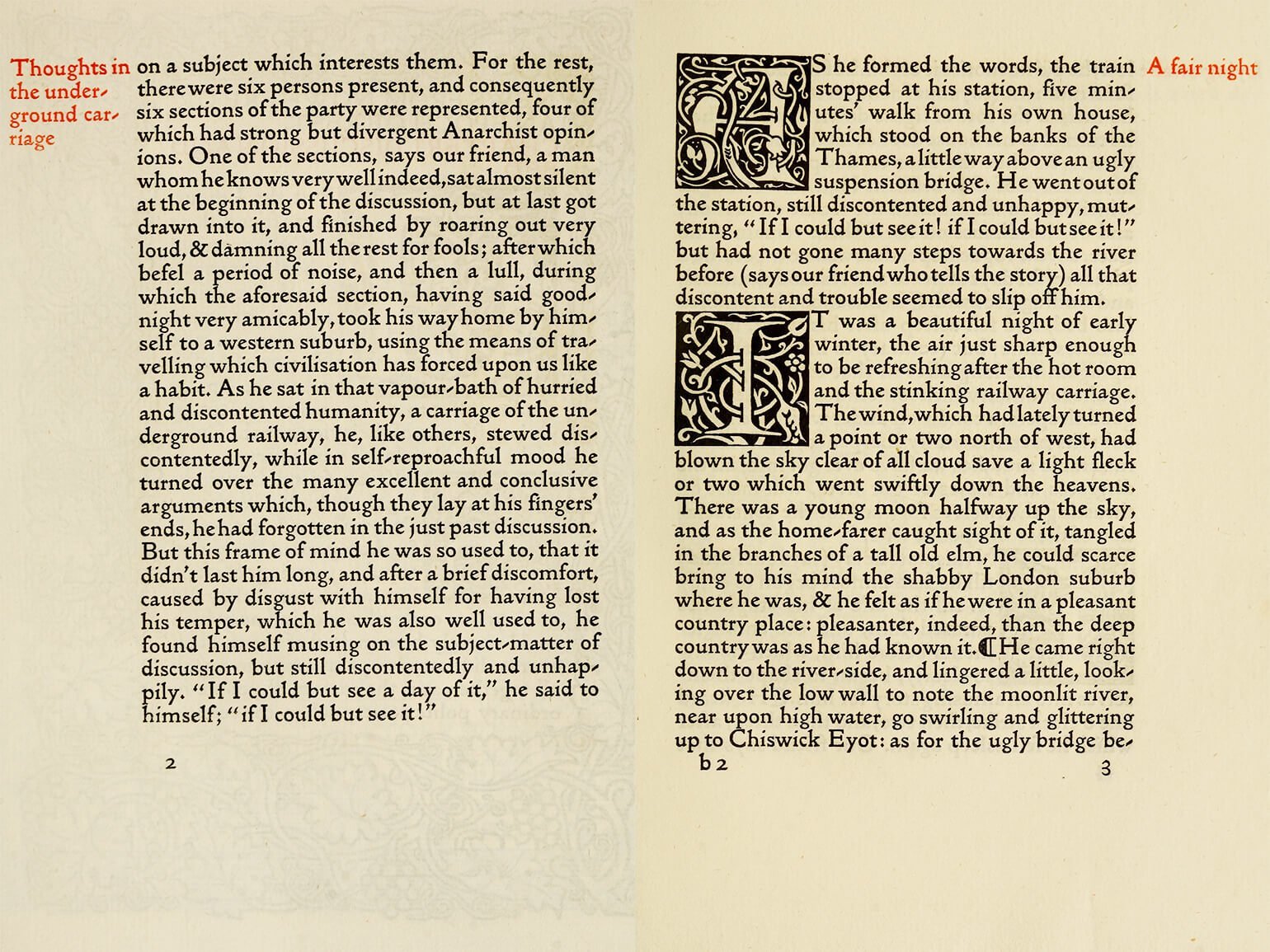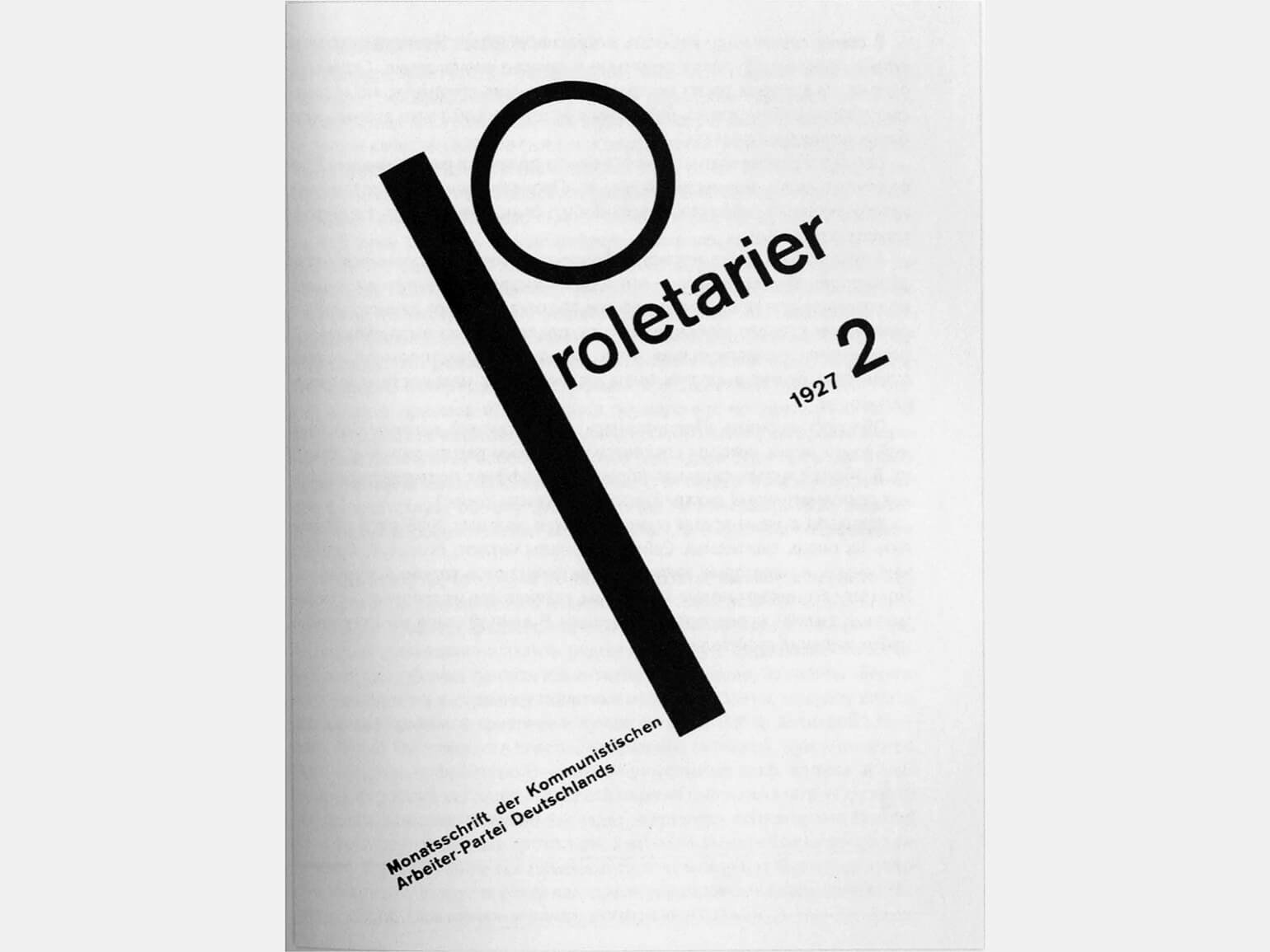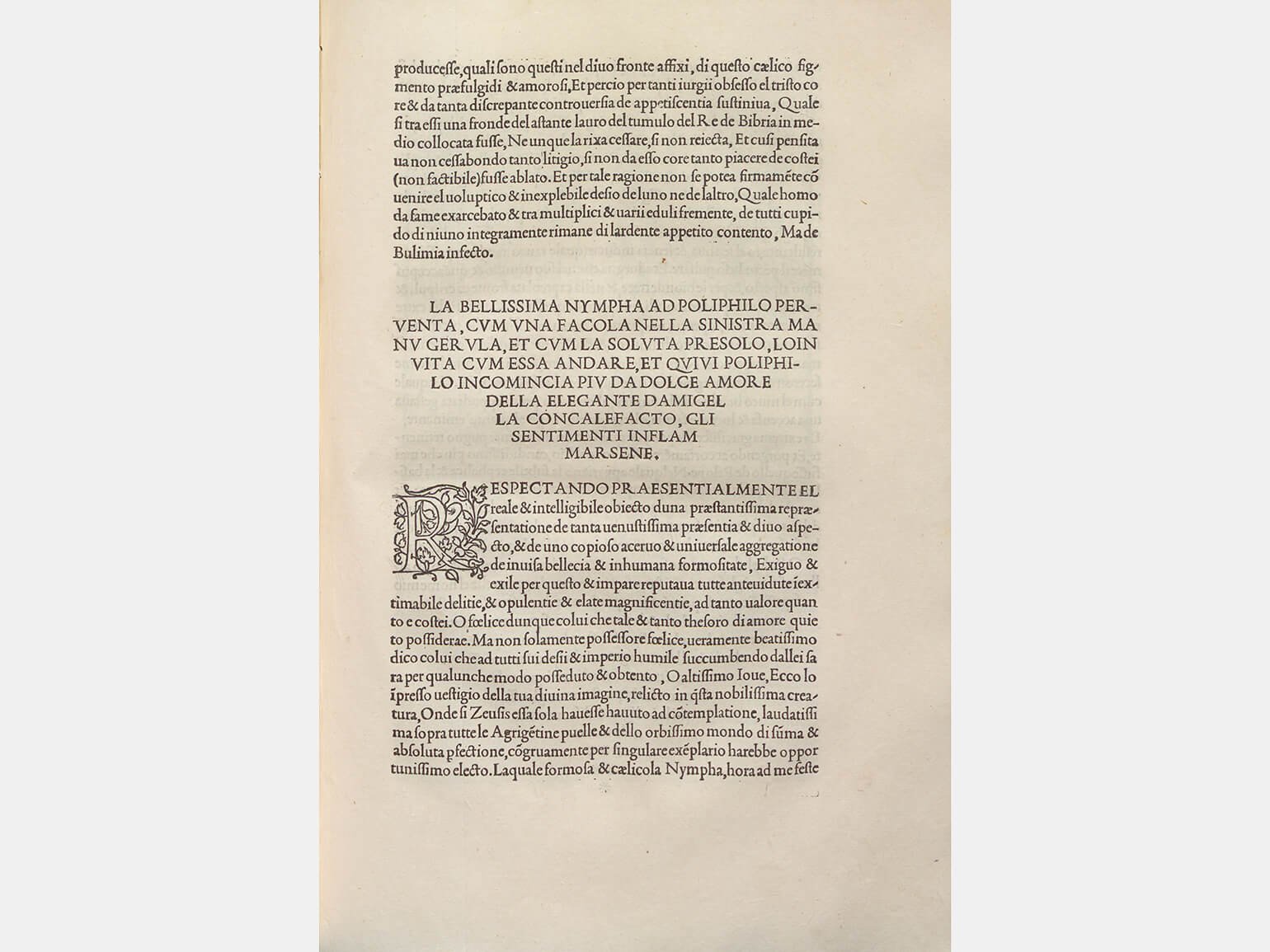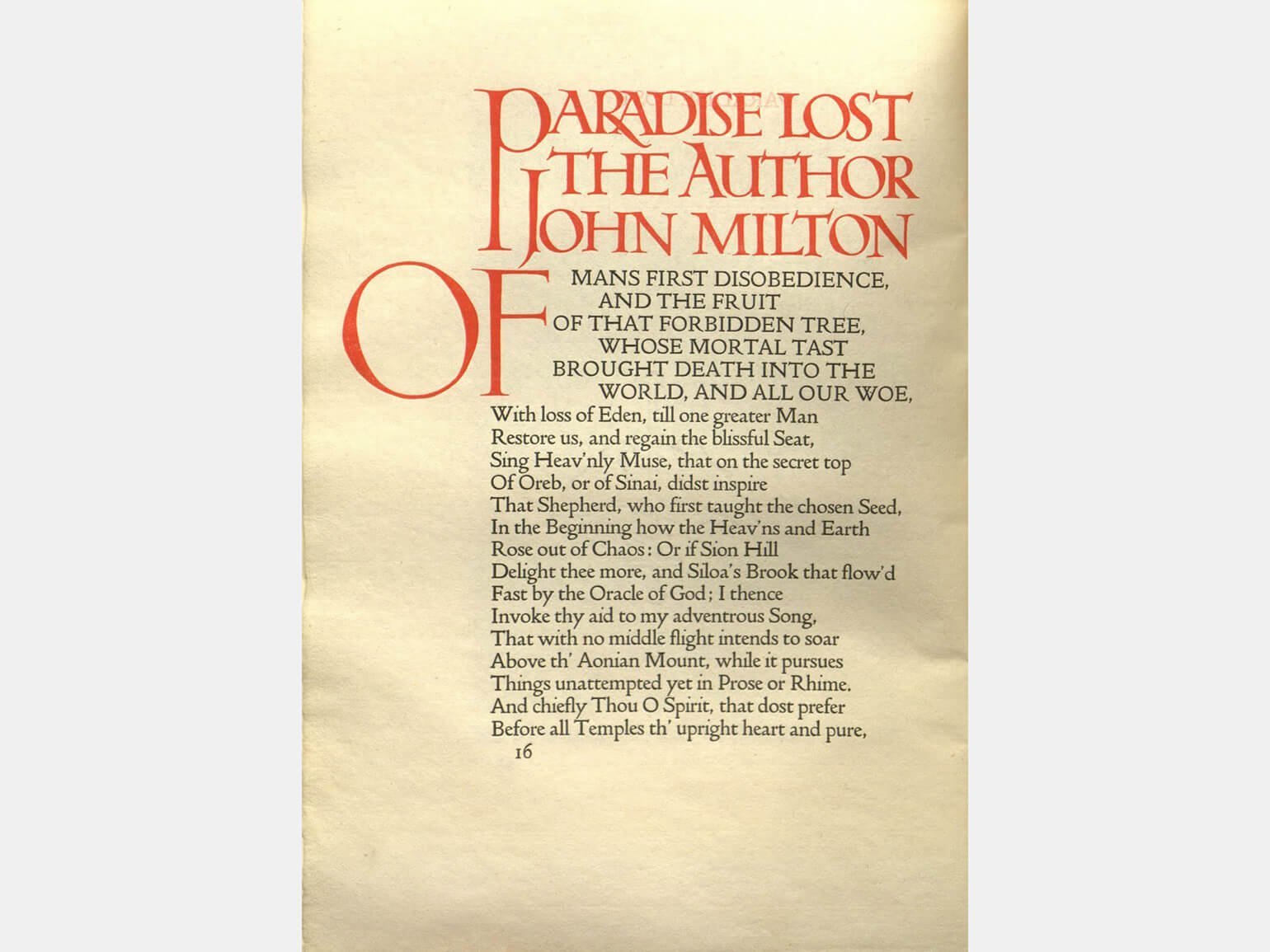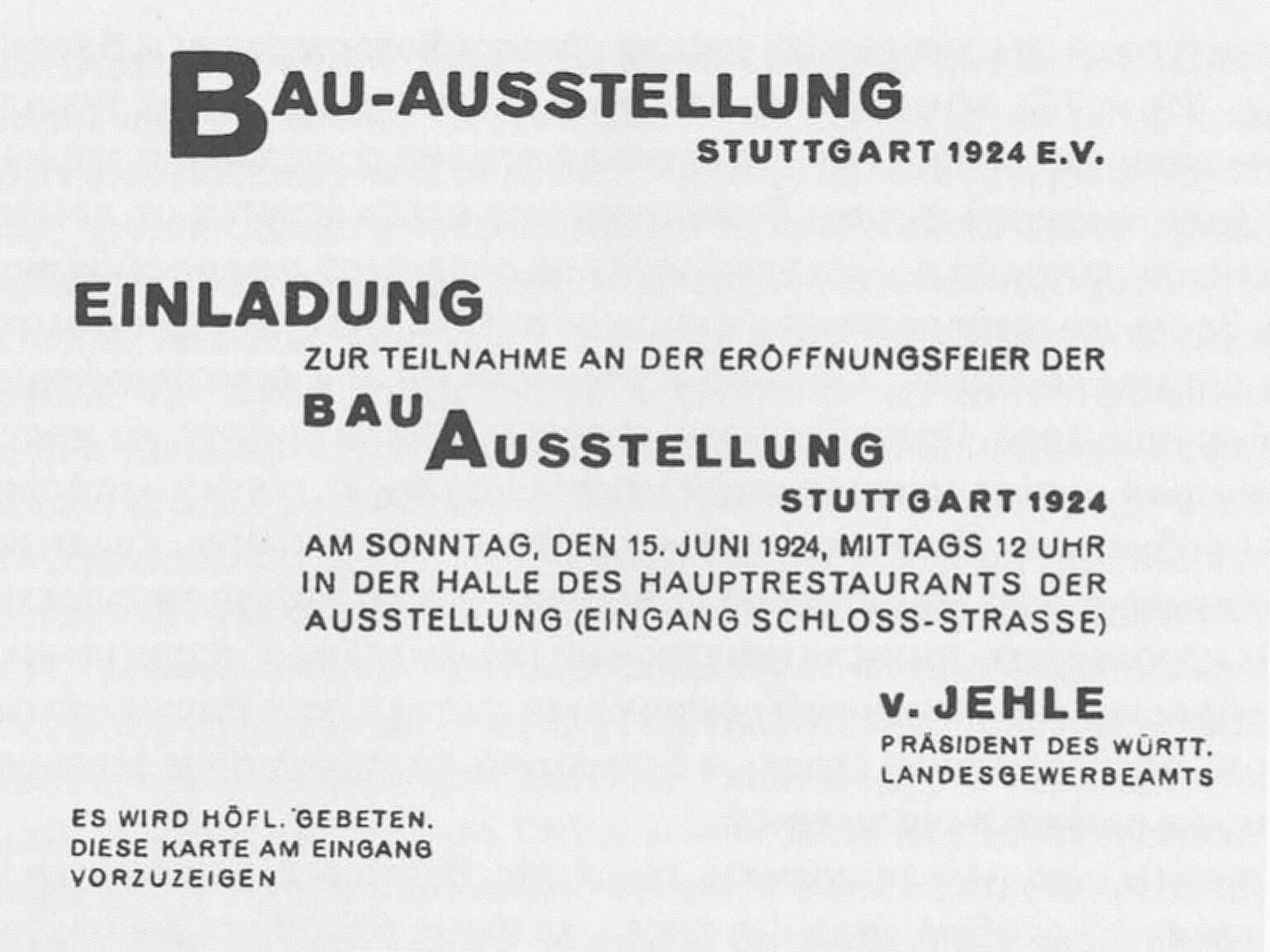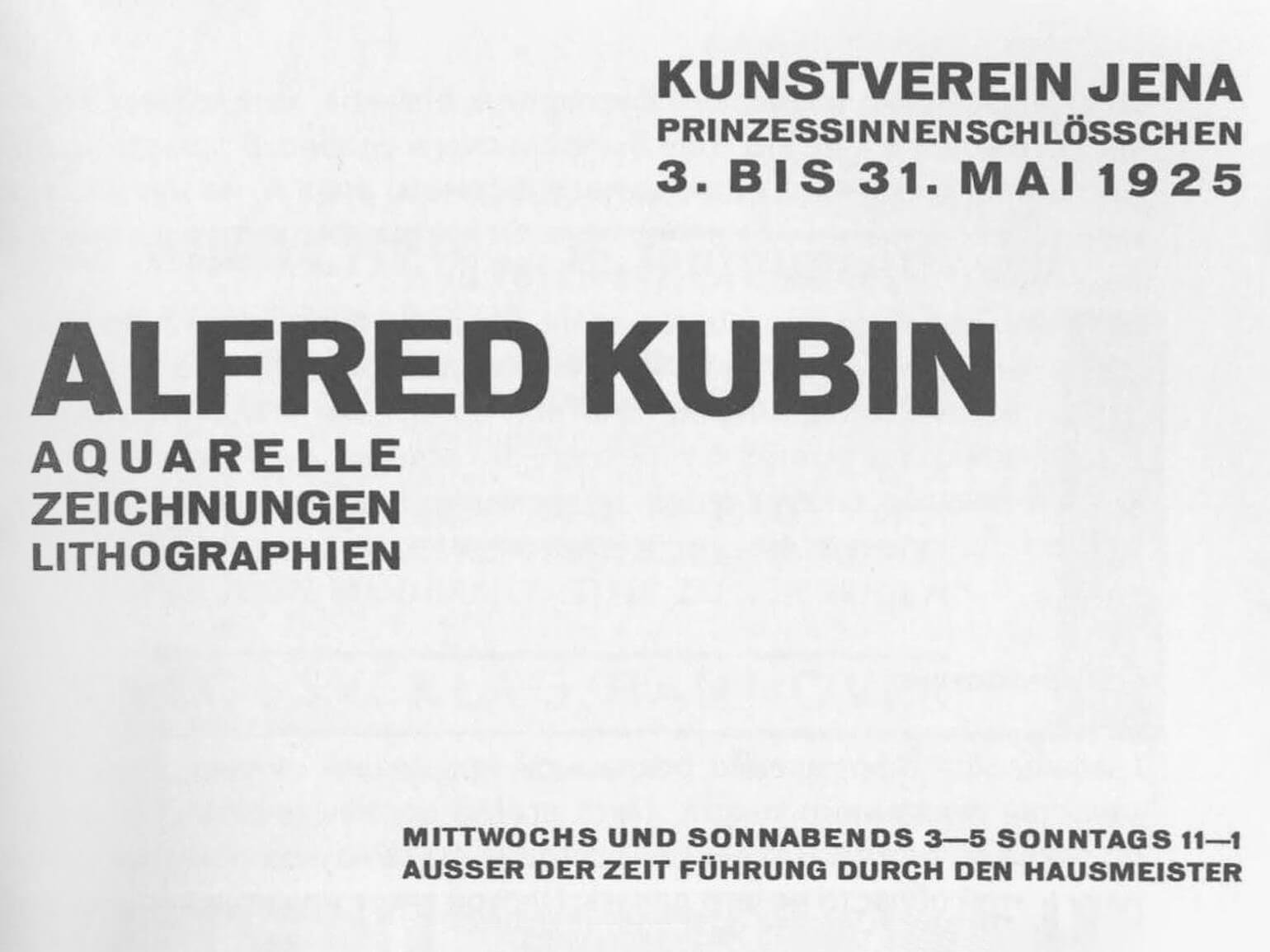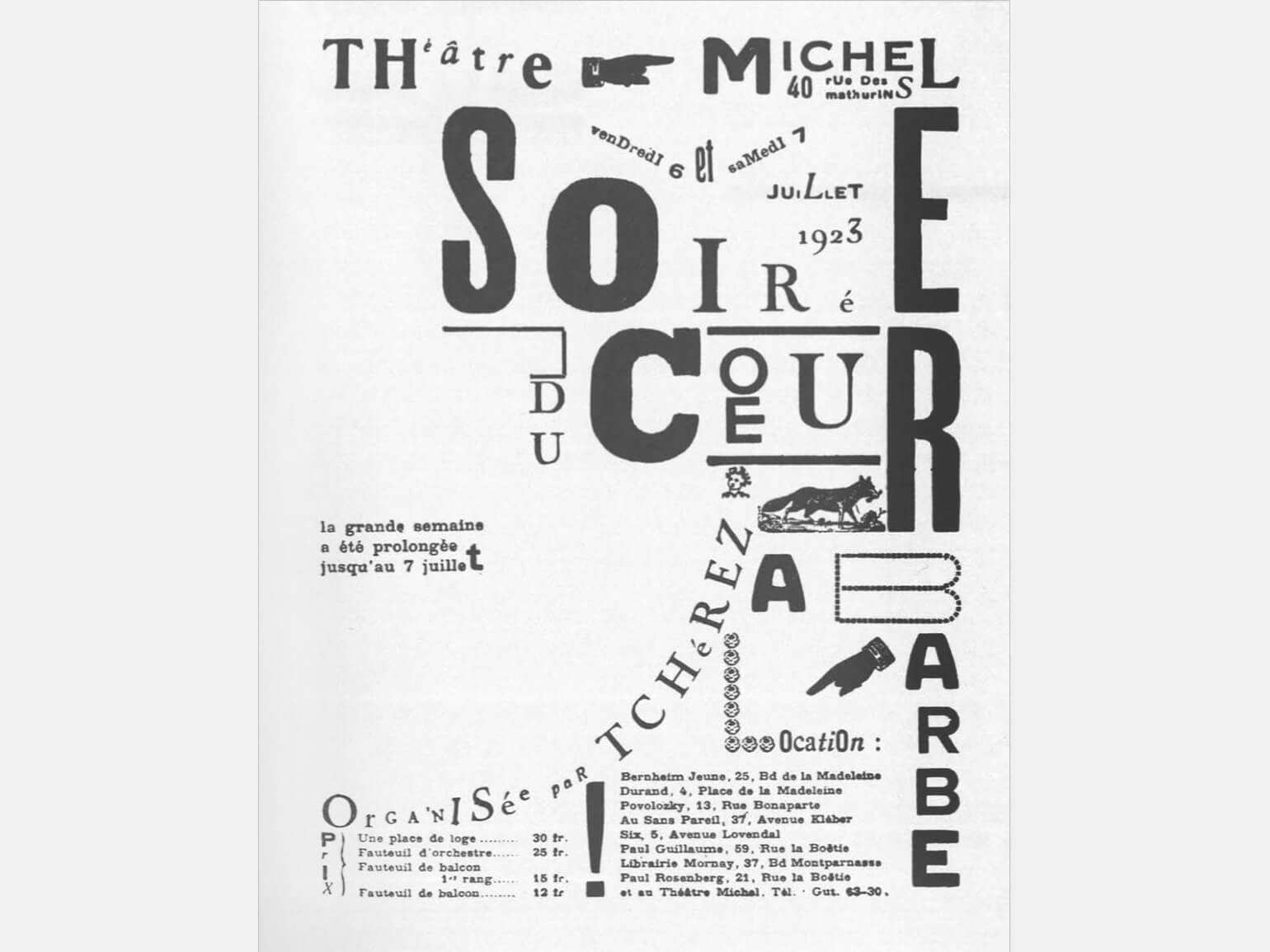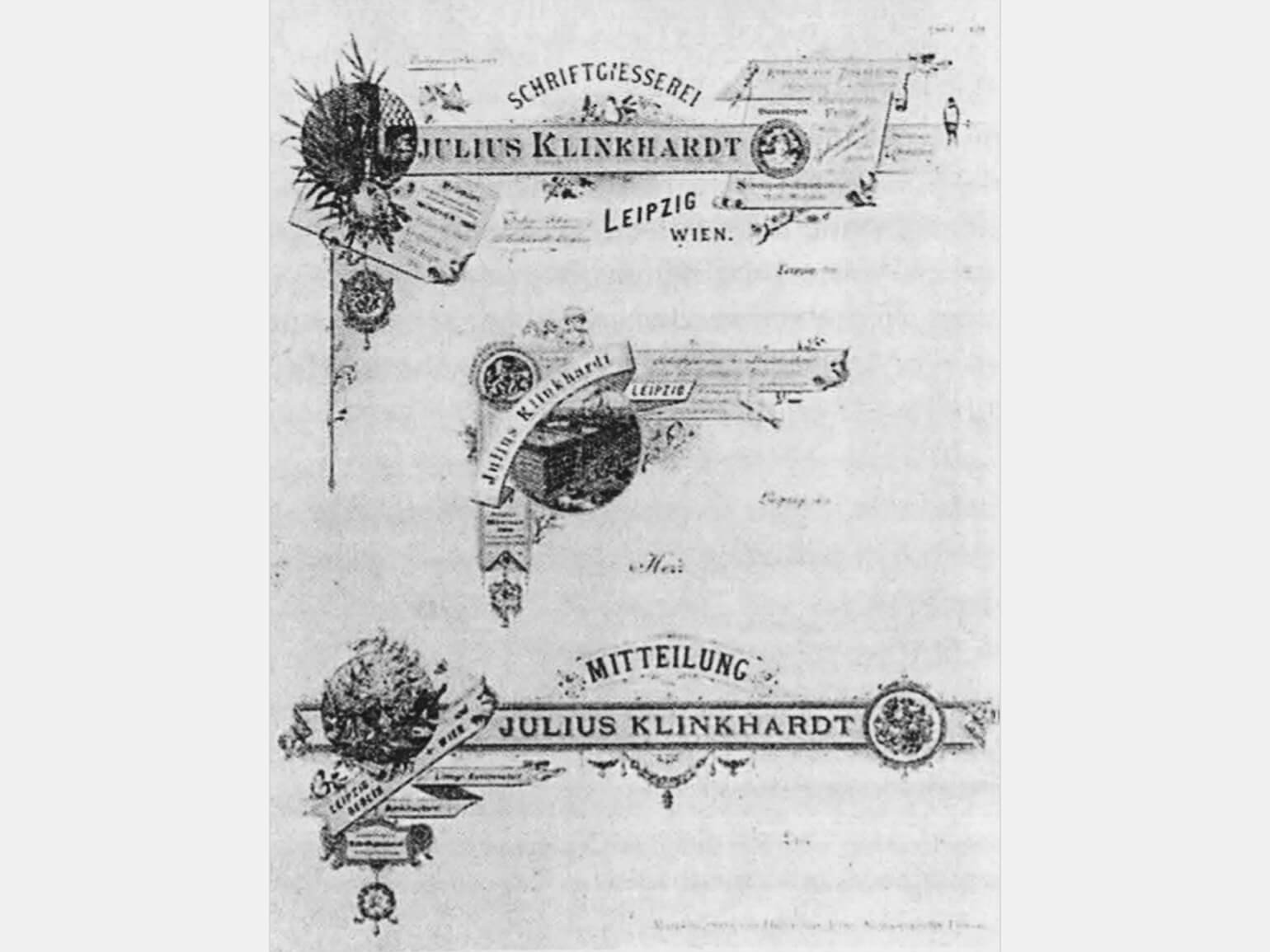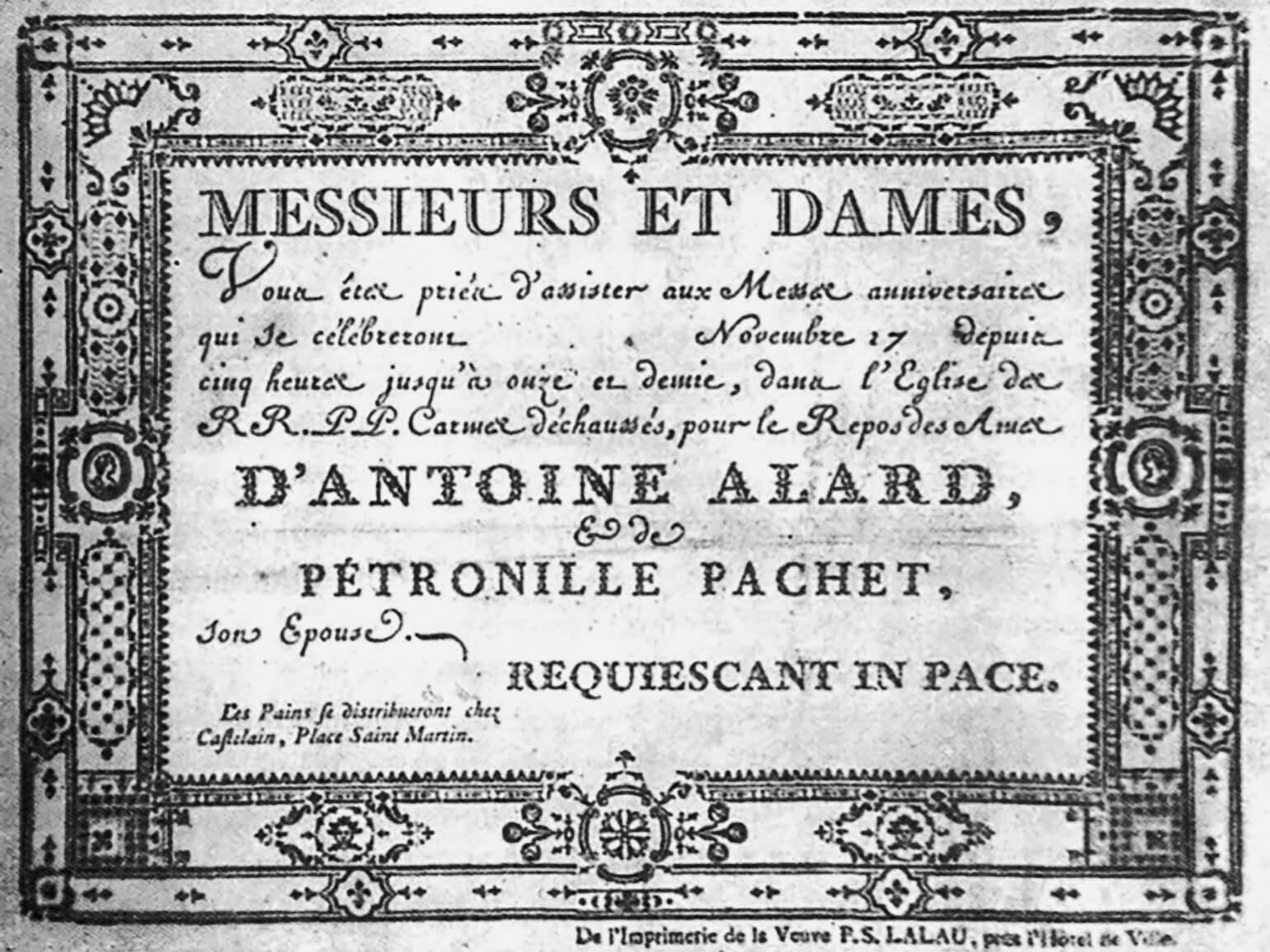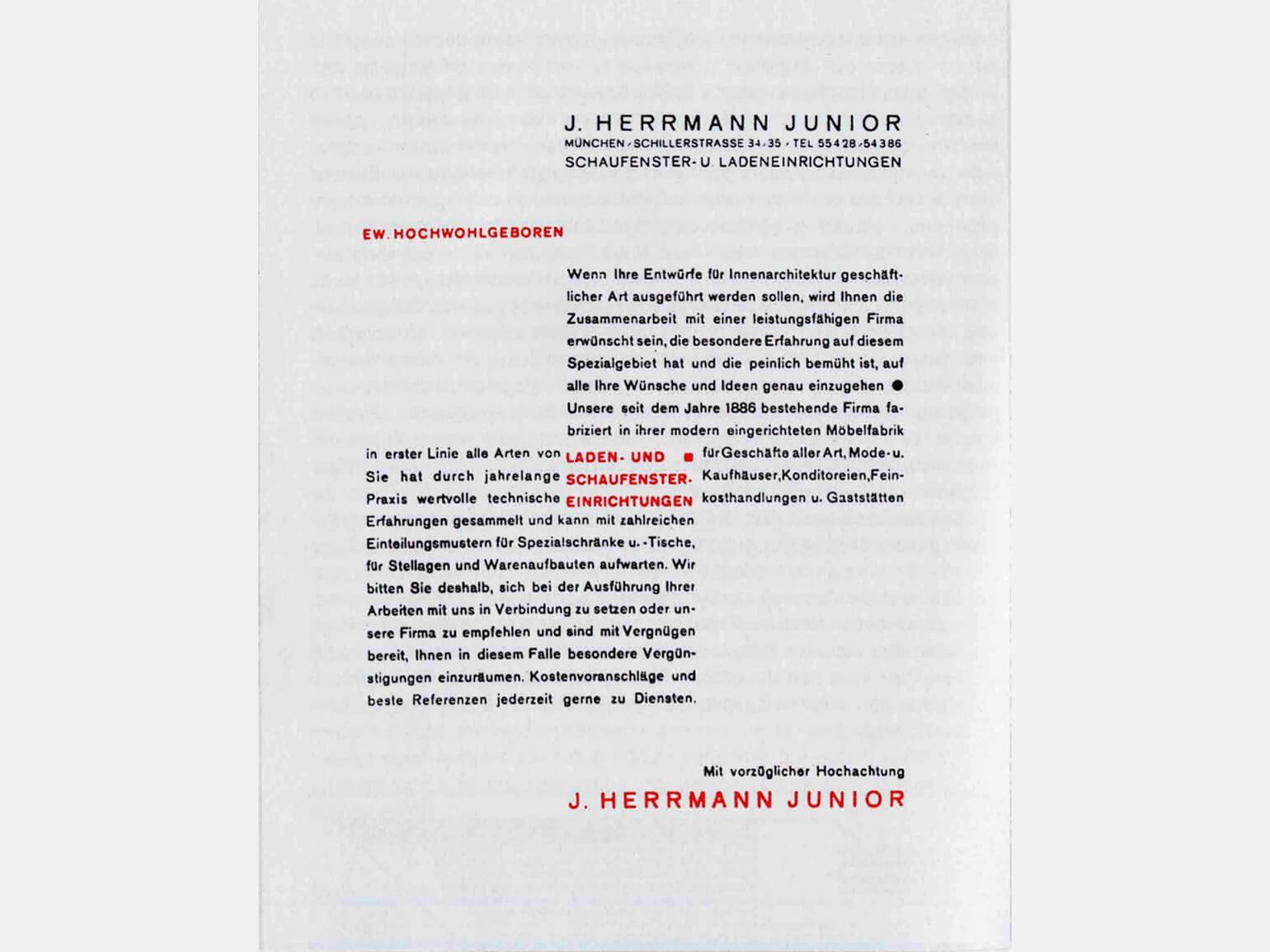
«Новая типографика»: правила ясной композиции
Рассказываем о том, как задачи текста влияют на его оформление.
В книге «Новая типографика» немецкий типограф Ян Чихольд рассказывает про переход от старых форм типографики к новым, а также о принципах работы с ними для создания визуально привлекательного текста.
Ян Чихольд — один из революционеров визуальной культуры. Он разработал и популяризовал принципы модернизма и усовершенствовал консервативную типографику. Чихольд работал в книжном деле более сорока лет. Он полностью изменил стиль оформления книг для Penguin Books, возродил несколько классических шрифтов и разработал стандарты книжной вёрстки.
Все советы из книги — пример видения Чихольда, актуального для первой половины XX века, когда была написана эта книга. Не стоит воспринимать их как законы типографики, но можно смело взять на заметку и применять в своей работе с информационными продуктами.
Новая типографика против старой
Человека окружает много информации — и на бумаге, и в интернете. А вот времени ознакомиться с ней очень мало. Чтобы не отставать от жизни, люди научились читать и рассматривать картинки быстрее. Информационные продукты подстроились под новое восприятие:
«Старая типографика и по своему интеллектуальному содержанию, и по форме была приспособлена для прежнего читателя, которому хватало времени спокойно и вдумчиво читать строчку за строчкой. В то время функциональность была не так важна.
Как правило, сегодня мы не читаем спокойно строчку за строчкой, а стараемся сперва пробежать весь текст целиком, а потом, если находим что-то интересное, изучаем это обстоятельнее».
Ян Чихольд
Чихольд отмечает, что прежних типографов больше волновала красота, оригинальность и эстетика своего продукта, нежели его удобочитаемость. Поэтому история типографики с середины XV века в основном описывает развитие шрифтов и орнаментов, а не ясности и чёткости печатного издания.
Чихольд уверен, что современным художникам стоит концентрироваться на простоте и лаконичности формы и чаще спрашивать себя: «Отвечает ли мой стиль функциям продукта?»
«Форма не существует сама по себе, а возникает из функции, используемого материала и конструкции».
Ян Чихольд
Мы привыкли удивляться красоте самолёта, автомобиля, парохода, хотя их совершенный облик — это точное и экономное выражение их функции. Чихольд считает, что основа новой типографики — минимализм, функциональность и отход от напыщенности.
Образец новой типографики. Минималистичная обложка журнала. Автор неизвестен
«Как архитектура освобождается от орнаментированных фасадов и декорированной мебели, создавая функциональные формы, так и типографика освобождается от псевдотрадиционных, давно устаревших схем».
Ян Чихольд
Принципы новой типографики
По мнению Чихольда, ясность — суть новой типографики. Она необходима, потому что сегодня мы перегружены объёмом информационной продукции. И в современных текстах требуется концентрация не на красоте, а на удобочитаемости.
Ясности мешает жёсткая симметрия. Она убивает композиционную логику текста:
«Не только принцип симметричного построения, но и вообще все заранее установленные формальные схемы противоречат сути новой типографики. Новая типографика отличается от прежней тем, что она пытается конструировать внешнюю форму, исходя из функций текста. Функции текста — передать смысл сообщения, выделить важные слова и сохранить логическую последовательность содержания».
Ян Чихольд
Это — верхняя часть бланка фирмы, торгующей книгами. Использование гротеска одинаковой жирности при симметричном построении не имеет никакого визуального эффекта и сегодня представляет собой «типографический ноль»:
Очень важно, чтобы типограф знал, как люди будут читать его работу. Это помогает принимать решения в композиции и выбирать те или иные шрифты. Например, чаще всего чтение происходит сверху вниз — в таком же порядке сменяют друг друга смысловые блоки текста.
«Любая часть текста связана с остальным текстом определёнными логическими отношениями, заданными с самого начала. Типограф должен придать им точную визуальную форму при помощи пропорций, размеров и плотности шрифтов, последовательности строк, цвета, фотографий».
Большинство текстов мы читаем сверху вниз и слева направо. Это общий закон. Сначала наше внимание привлекает заголовок, а затем — остальные части текста в зависимости от важности. Если работать над текстом по этим принципам, можно ощутить ритм асимметрии, характерный для новой типографики.
Пригласительный билет и афиша ниже — хорошие примеры того, как типографика направляет взгляд читателя в нужную сторону и помогает быстро считать информацию:
Образец схематичной формы